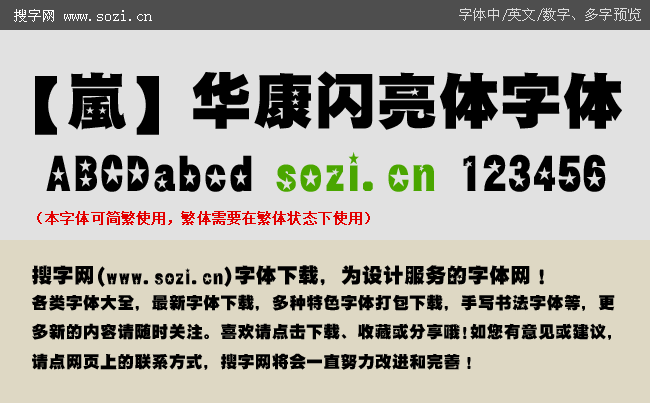
閃亮體字體
搜字網(wǎng)給大家提供一款很有趣的手機(jī)中文字體下載。修改者給他起名為閃亮體字體,這款手機(jī)字體是在粗黑體字體筆畫間插入了閃閃的卡通星星圖案。在保留黑體粗重厚實(shí)的風(fēng)格同時(shí),又具備趣味性,特別適合喜歡手機(jī)字體個(gè)性一些的朋友在手機(jī)上安裝使用。